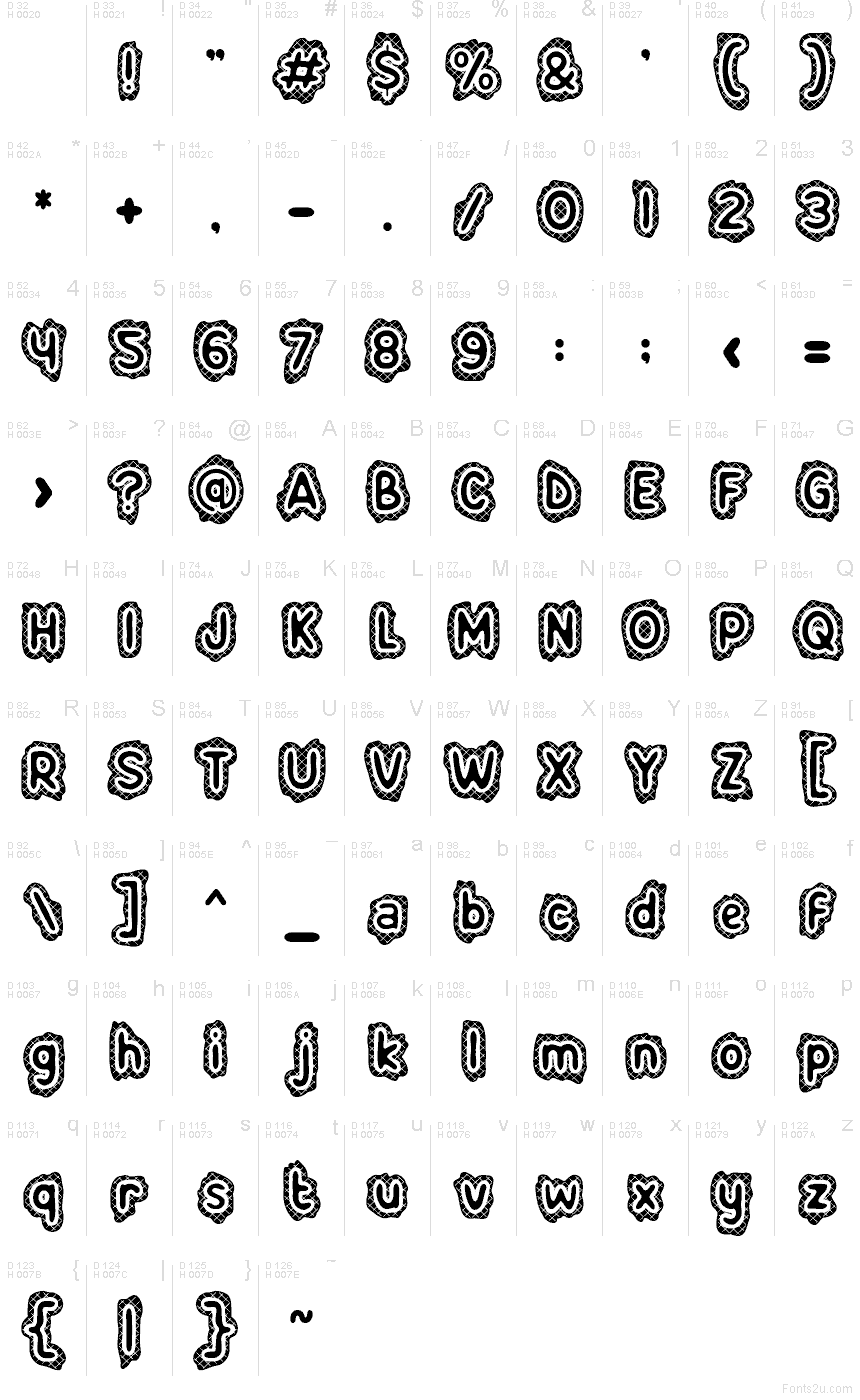
Cake Couture Three
Cake Couture Three von Putracetol Studio ist eine kostenlose Display-Schriftart im Bakery-Stil, die durch ihre weichen, puffigen Buchstaben und eine handgemachte Optik besticht. Die Zeichen wirken wie mit dickem Zuckerguss überzogen, während das kreuzweise Muster in jedem Buchstaben dem gesamten Alphabet einen gesteppten, süßen Charakter verleiht – verspielt statt perfekt poliert.
Sie passt perfekt zu Markenauftritten von Bäckereien, Café-Menüs, Einladungskarten, Sticker-Designs und fröhlichen Verpackungen, wo eine kostenlose Schriftart mit dieser zuckrigen Textur auch kurze Wörter für sich allein stehen lassen kann. Verwenden Sie sie für Cover-Texte, Produktnamen, Titelkarten oder kleine Überschriften, wenn die Schrift aussehen soll, als wäre sie frisch glasiert, vernäht und ein wenig handgemacht.